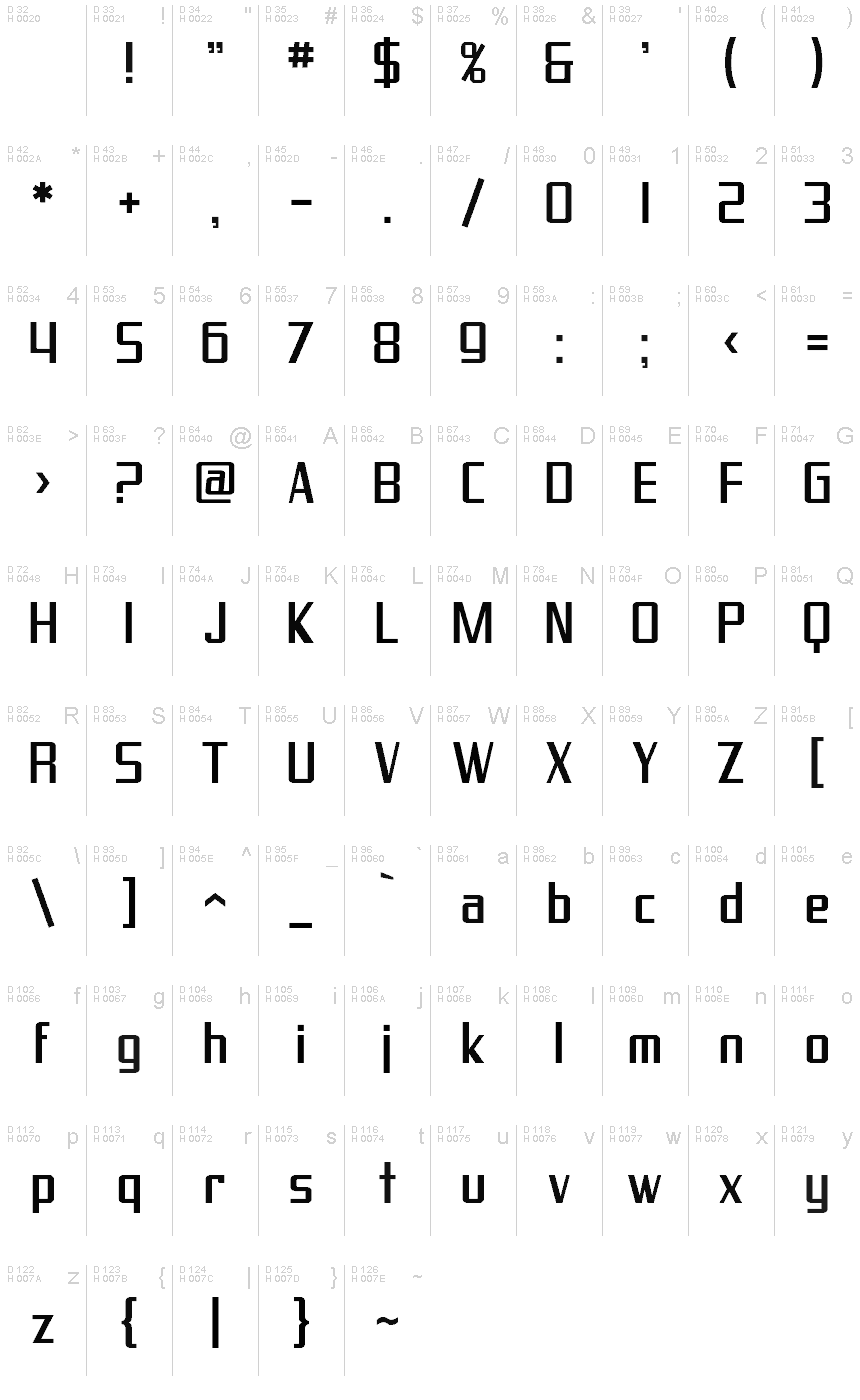
SF Proverbial Gothic
SF Proverbial Gothic, nata dalla ShyFonts Type Foundry, rappresenta una convergenza unica tra lo stile techno e la sensibilità gotica. Come font display a larghezza semi-condensata, offre un'estetica tanto sorprendente quanto funzionale. Le sue linee pulite e il tocco moderno, sottolineati da una precisione architettonica, la rendono ideale per progetti che cercano di trasmettere forza ed eleganza contemporanea.
Lo stile techno di SF Proverbial Gothic infonde in ogni testo un taglio dinamico, rendendolo particolarmente adatto a branding innovativi, contesti hi-tech o qualsiasi iniziativa creativa che richieda un font con carattere e impatto visivo. La natura semi-condensata garantisce un'ottima leggibilità sia su carta che su media digitali: perfetto per titoli, poster o qualsiasi spazio in cui si voglia far risaltare il proprio messaggio.
La versatilità di SF Proverbial Gothic non risiede solo nel suo fascino visivo, ma anche nella sua capacità di adattarsi a diversi scenari di design. Che puntiate a una sofisticazione minimalista o a creazioni audaci, questo font trasformerà la vostra visione in una realtà che cattura lo sguardo.
SF Proverbial Gothic — Presentazione del carattere